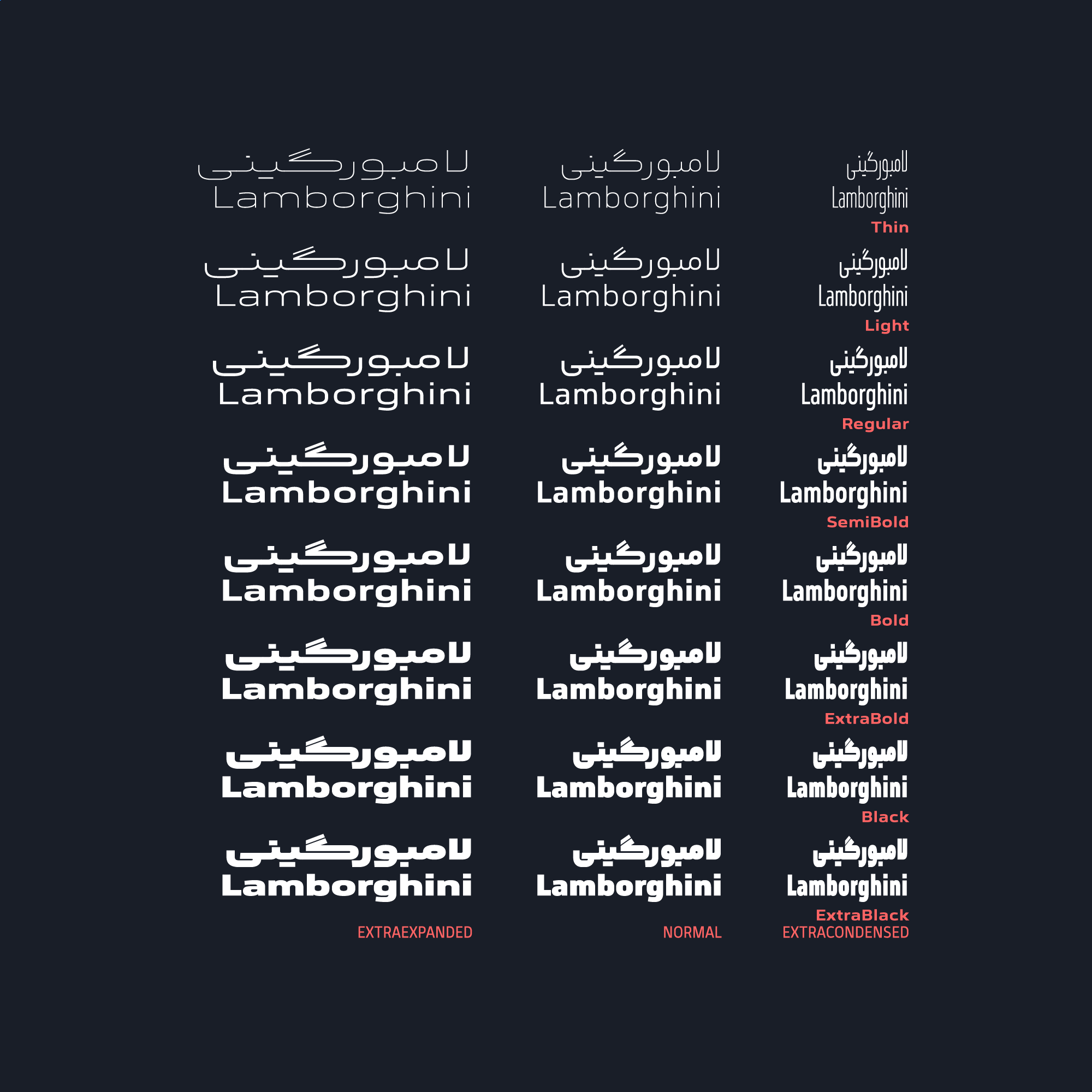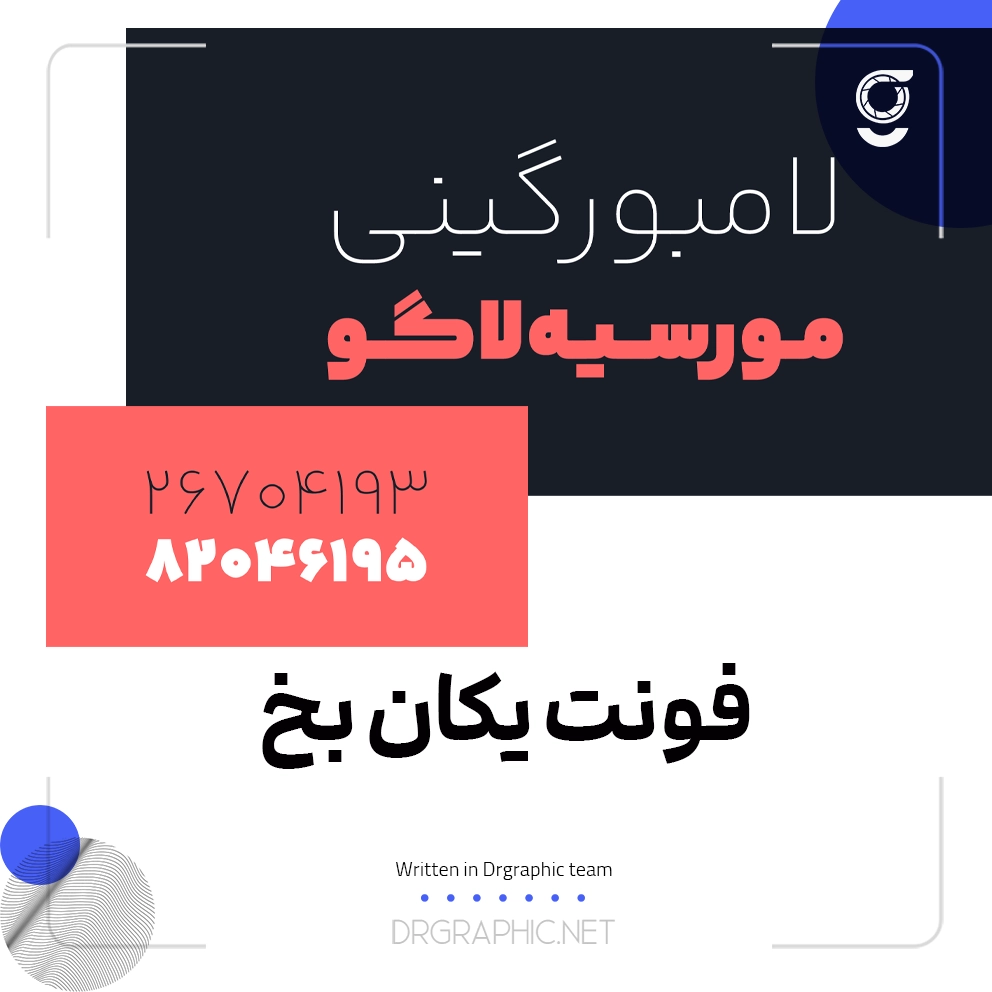
فونت یکان‌بخ برای نیاز امروز طراحی شده است، چراکه فونتی است ساده، خنثی، ویژه‌ی فضای پیکسلی و مناسب برای فضاهای چاپی. این ویژگی‌ها باعث شده تا فونت یکان‌بخ در موقعیت‌های مختلف کارآمد و بدون دردسر عمل کند.با دکترگرافیک همراه باشید.
در یکان‌بخ همه‌ی کاراکترها به‌شکل اغراق‌آمیزی ساده طراحی شده است. جزئیات تا جای ممکن حذف شده‌اند و حرکت‌ها ساده‌سازی شده است.
یکان‌بخ در دسته‌ی فونت‌های مونولاین (تک‌ضخامتی) قرار می‌گیرد اما به‌طور کامل دارای ضخامت یکسان نیست. این‌جا خطای دید نقشی پررنگ بازی می‌کند و آگاهی از تأثیر زاویه‌ی قلم نیز بسیار مهم است. در سر هر پیچ و هر تقاطع ضخامت‌ها با دقت بسیار زیاد طوری تنظیم شده‌اند که درست دیده شوند.
در طراحی یکان‌بخ از فرم‌های هندسی کمک گرفتیم، اما خود را به استفاده از آن فرم‌ها محدود نکردیم و کاراکترها به‌طور کامل با فرم‌های هندسی منطبق نیستند. دلیل این کار حفظ خوانایی و در نظر گرفتن خطای دید در طراحی بود. هم‌چنین فرم‌های هندسی باعث می‌شوند حروف شخصیتی سرد و ماشینی به‌خود بگیرند؛ به‌ویژه در رسم‌الخط عربی که چندان با فرم‌های هندسی میانه‌ای ندارند.ج